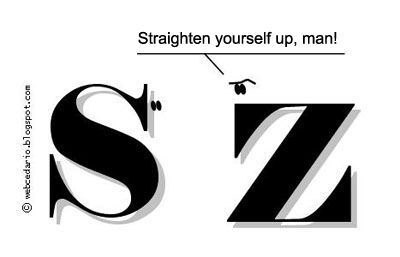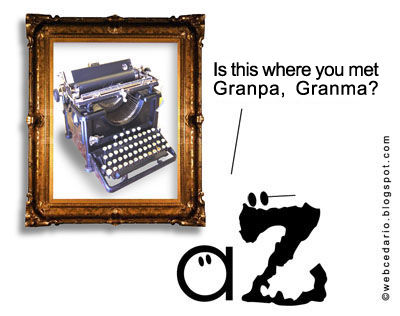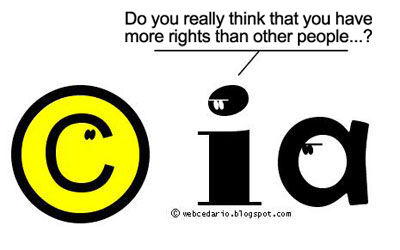
Buchstaben-KarikaturenDer portugiesische Designer ABC Darius betreibt eine Internetseite,
auf der wöchentlich ein Typo-Comic erscheint. Die Buchstabenkompositionen
erinnern bisweilen an die typografische Kunst El Lissitzkys, wobei Darius
auf jeglichen politischen Symbolismus verzichtet. Bei ihm stehen die
alltäglichen Sorgen der Groß- und Kleinbuchstaben im Mittelpunkt ...
![]() ABC
Darius ist männlich, Sternzeichen Steinbock und angeblich 93
Jahre alt ... wobei es sich hier sicherlich um einen Zahlendreher handelt. Seine
typografischen Illustrationen, von denen im Durchschnitt eine pro Woche
erscheint (RSS-Feed), nennt er Talking Letters. Sie
erinnern bisweilen an die Collagen des russischen Künstlers El
Lissitzky, Mitbegründer des Konstruktivismus. Mit seiner
Ablehnung des linearen Gutenbergschen Bleisatzes sah El Lissitzky früh die
Wende zum Fotosatz voraus. Bekannt ist seine Webekampagne für
Pelikan.
![]() El-Lissitzky-Plakat für Pelikan Typografische Illustrationen von ABC Darius: ![]() Glauben Sie wirklich, dass Sie mehr Rechte haben als andere? ![]() Und da hast Du Oma getroffen, Opa? ![]() Mensch, nehmen Sie Haltung an! Herausgegeben: Mi - August 3, 2005 at 02:17 nachm. | |